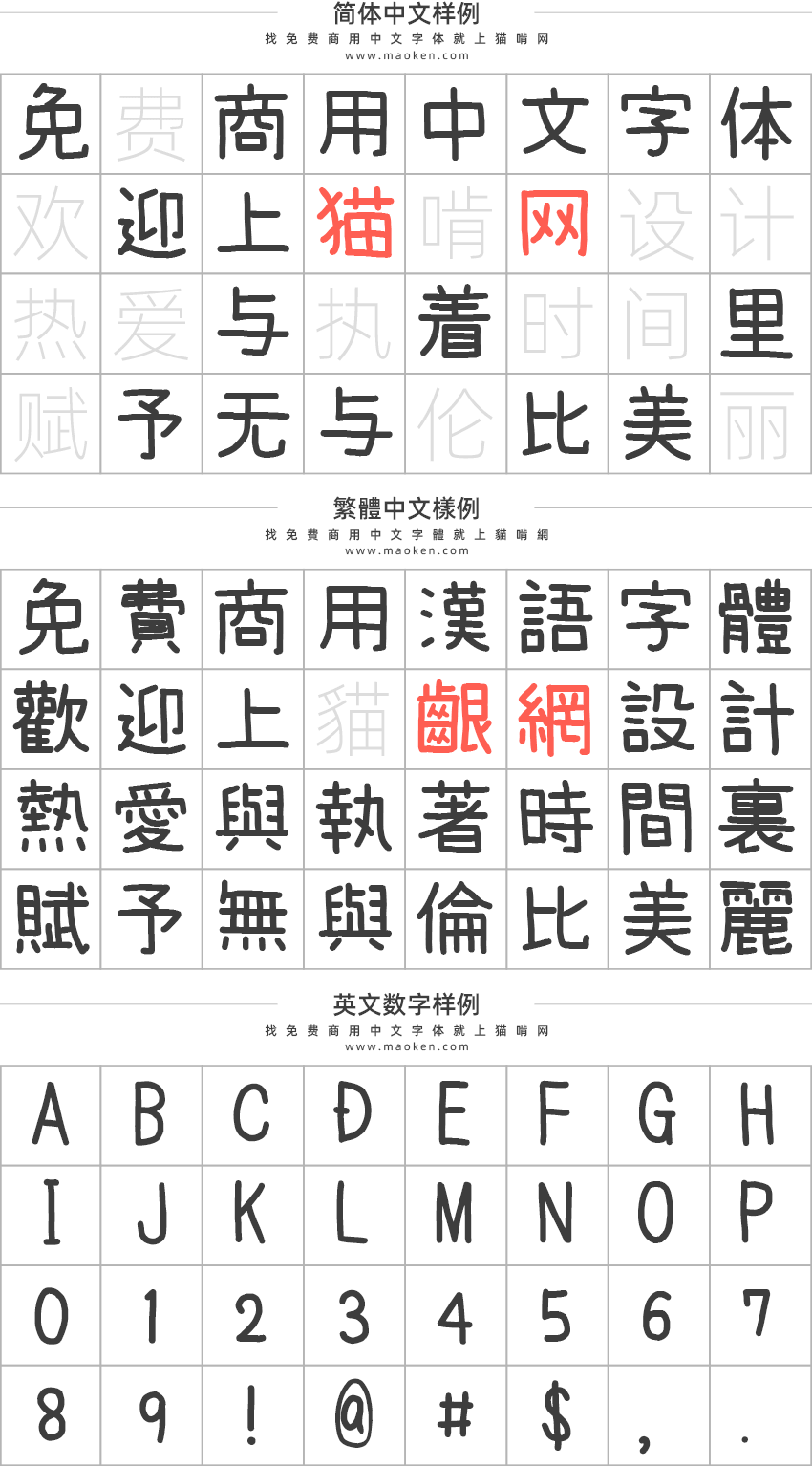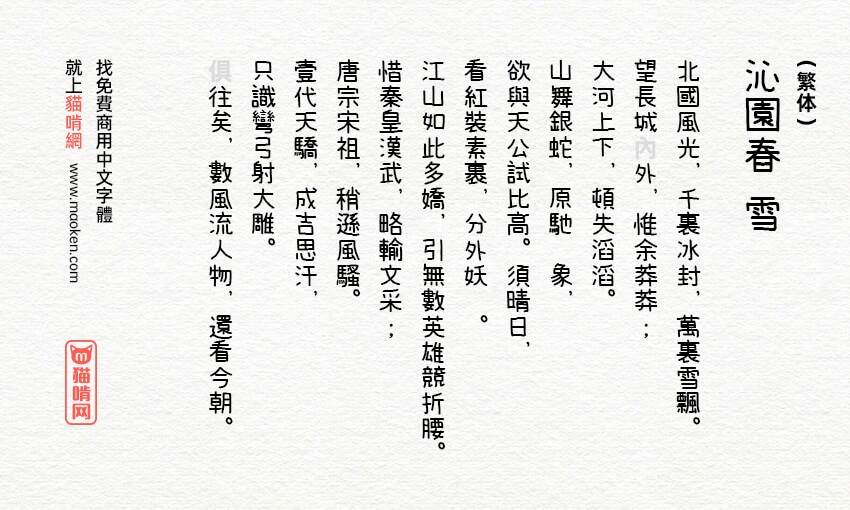
梅干手写体:适合休闲的设计且易阅读的日系手写字体
梅干手写体是日本设计师“toga”先生创建的手写免费商用字体,精心书写的圆字非常容易阅读,非常适合休闲的设计。
梅干手写体收录了平假名、英文数字、半角·半角英文数字、符号、JIS第一、第二水准、IBM扩展汉字。 简体字数不算多,但是繁体则比较齐全。